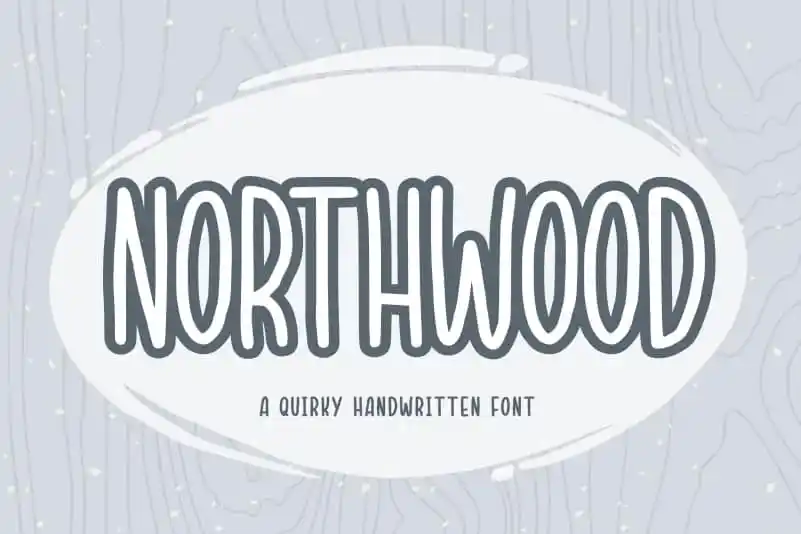
Northwood Quirky Handwritten Font – Fonte Grátis
Northwood Quirky Handwritten Font
A Northwood Quirky Handwritten Font é perfeitamente adequada para uma variedade de projetos criativos no Brasil, sejam eles tipicamente brasileiros ou internacionais. A fonte leva seu design elegante e peculiar para ambientes como embalagens de produtos, identidades corporativas, revistas, redes sociais, casamentos e muito mais. Com seus traços fluidos e características únicas, a Northwood permite que você expressione sua criatividade de maneira única em qualquer projeto, tornando-a perfeita para quem busca algo diferente e atraente para decorar o fundo ou destacar as palavras em seu trabalho gráfico. Nesse contexto brasileiro vibrante e diversificado, essa fonte irá trazer um toque especial a cada projeto que ela encorajará.